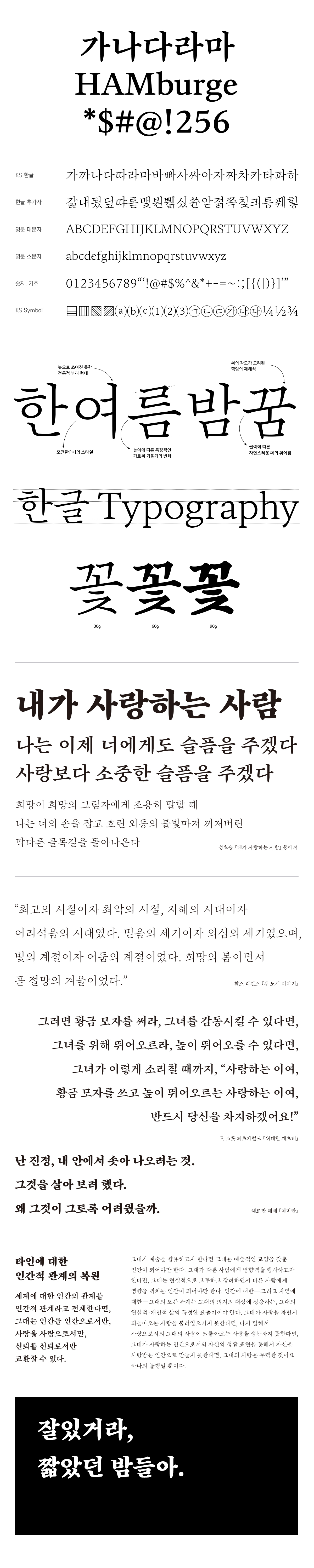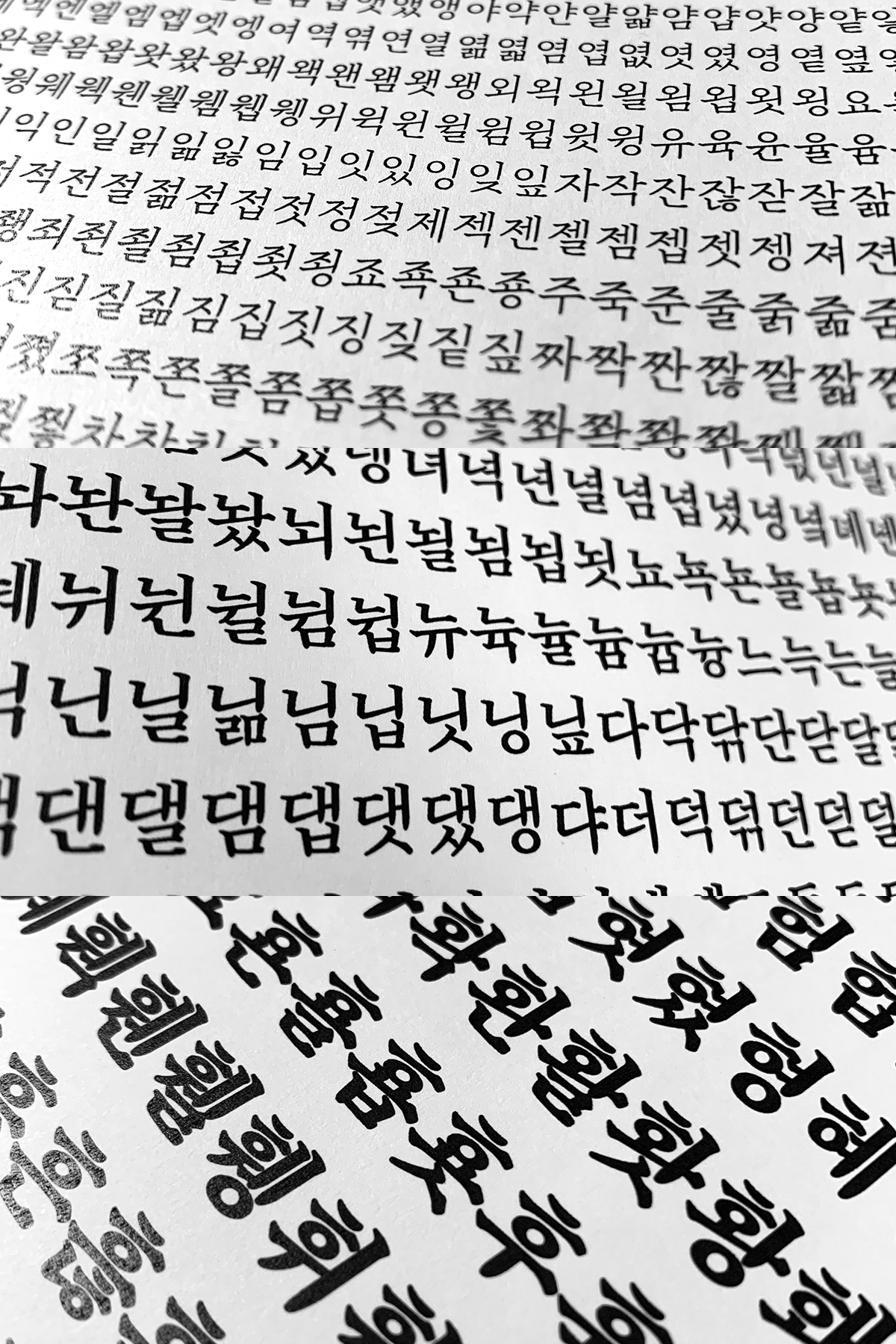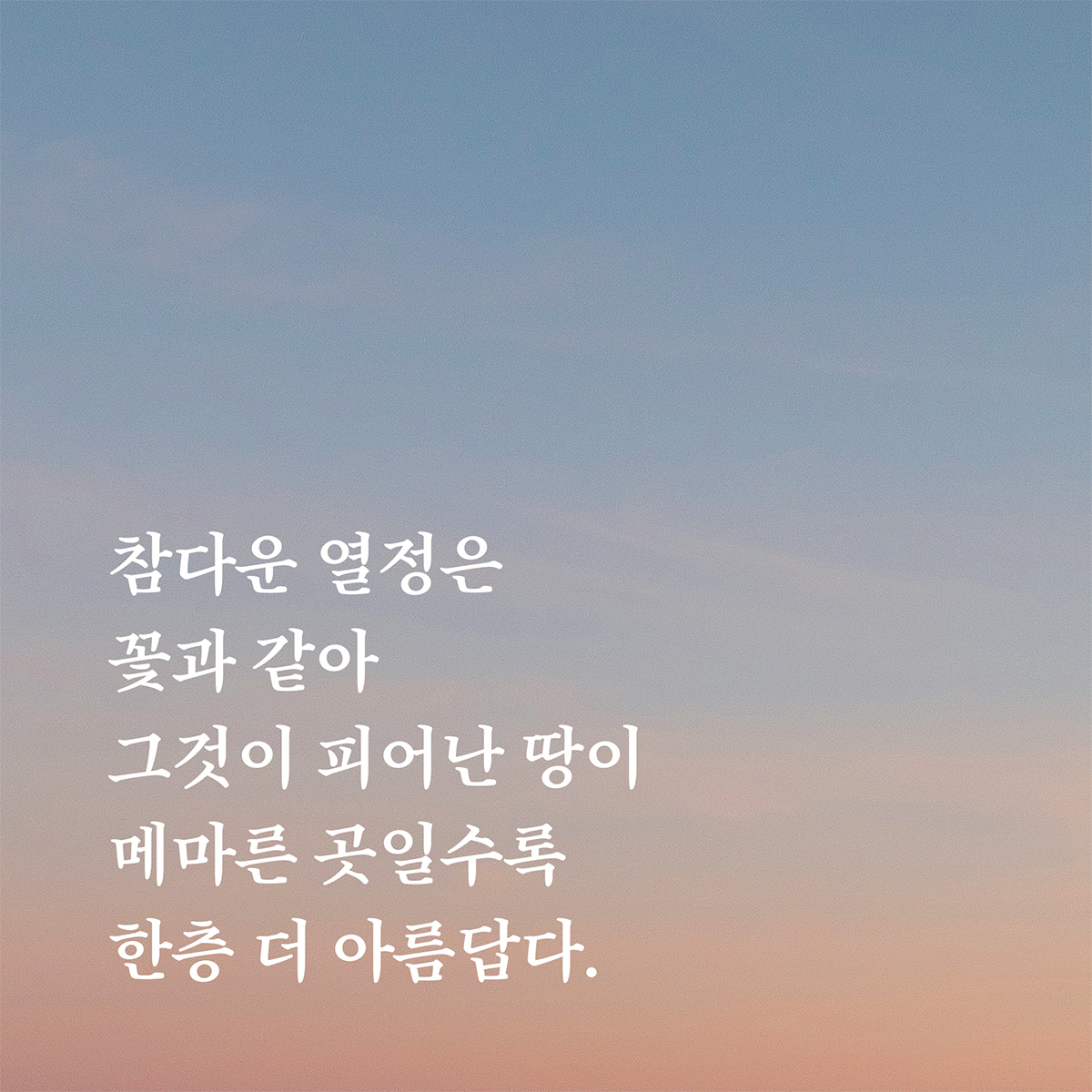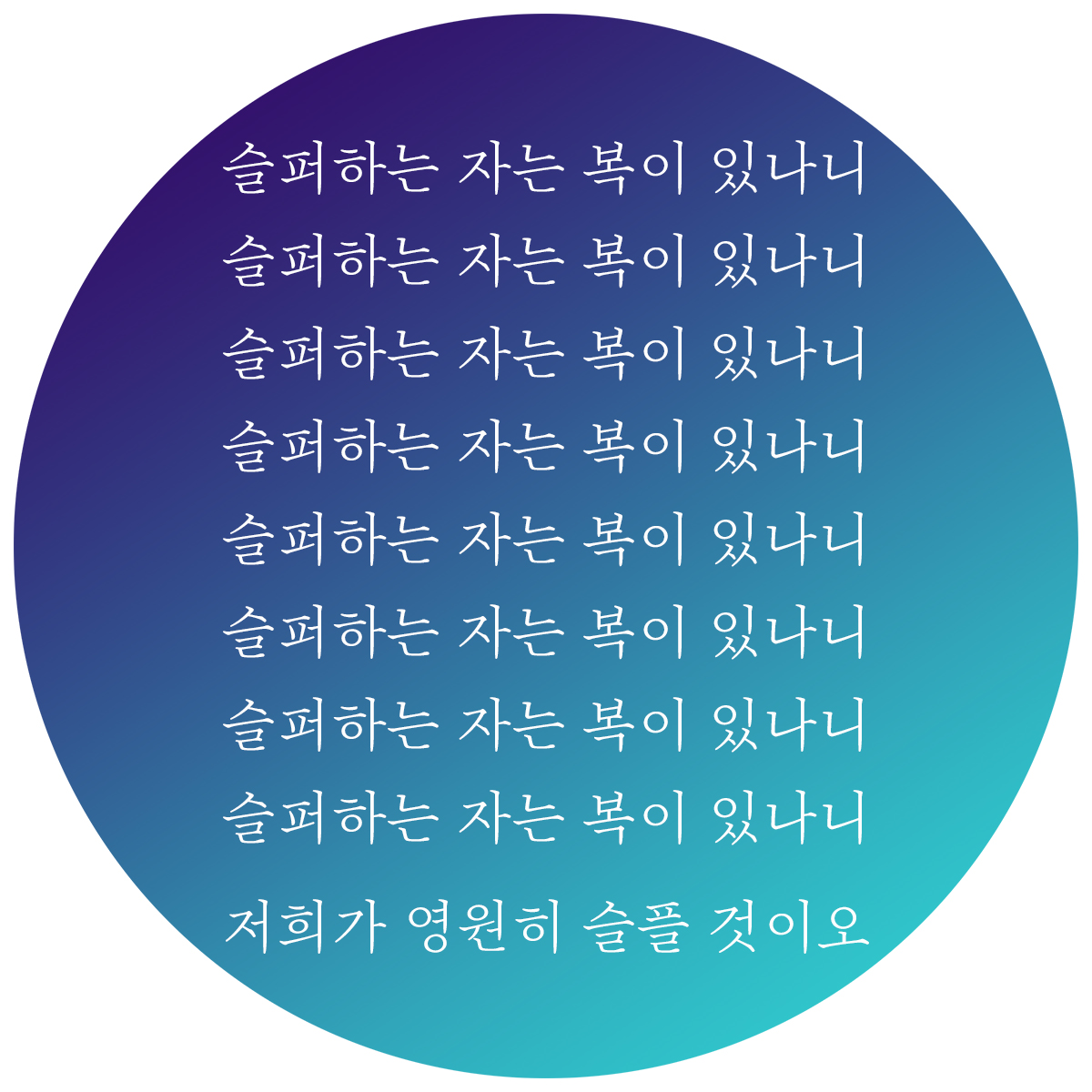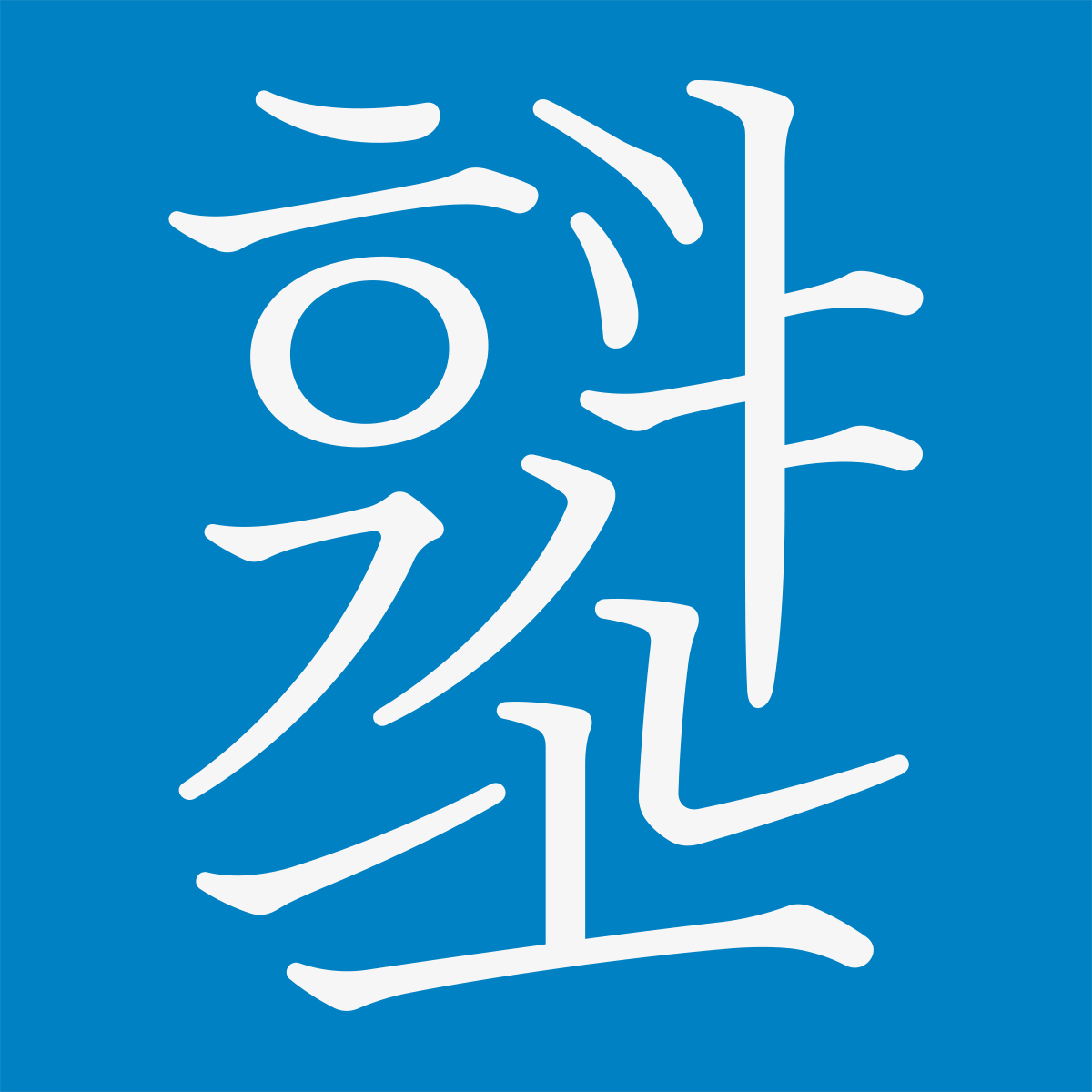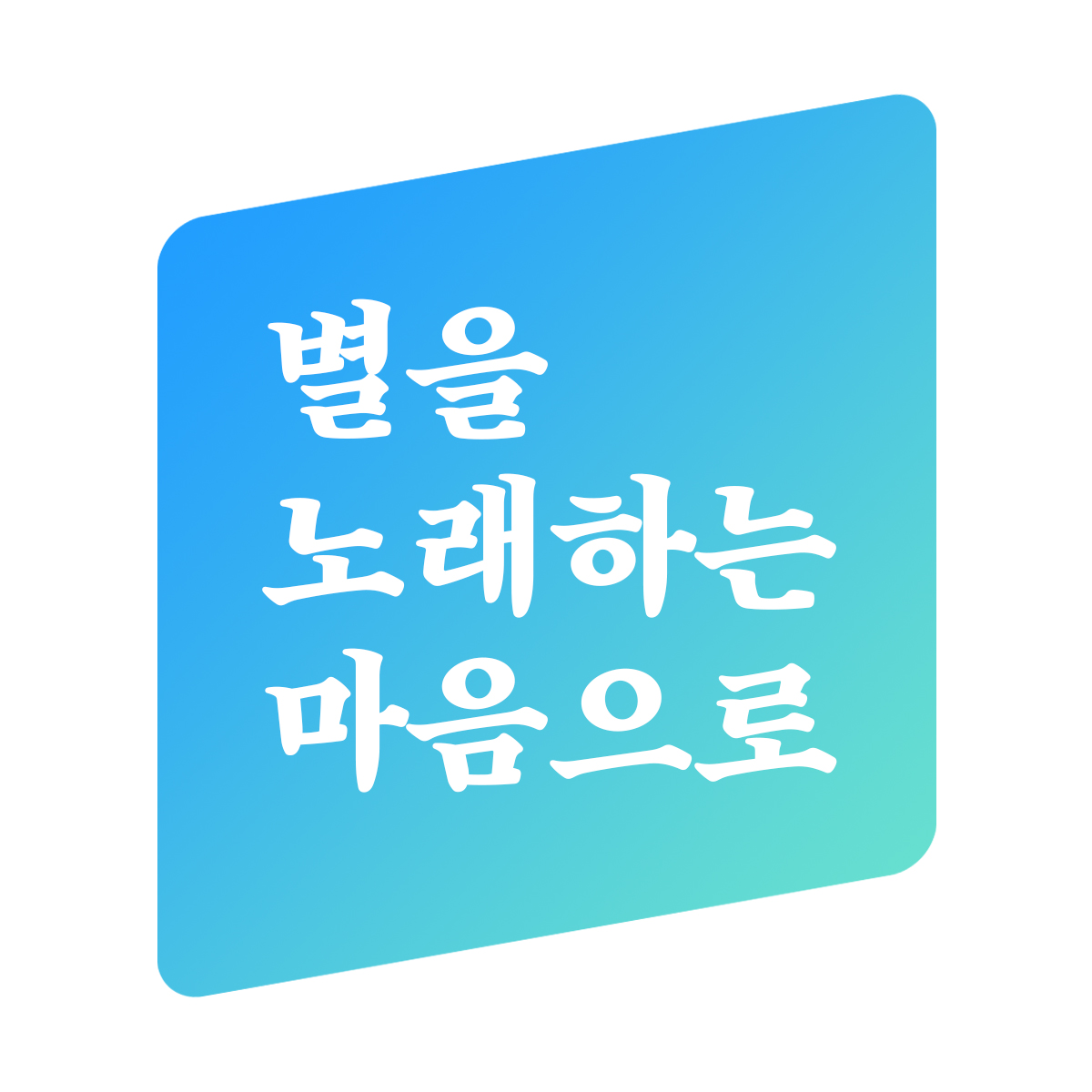
3가지 웨이트의 패밀리로 구성되어 있으며, 11,172자의 한글 글립이 모두 디자인되어 있습니다. 낱글자의 형태와 구조가 비교적 다양하게 디자인되어 있어서 그에 맞는 글자 너비가 적용된 가변폭으로 제작되었습니다. 영문 디자인은 한글 궁서체의 획 순을 연구하여 영문 서체에 적용하였습니다. 때문에 일반적인 영문 서체의 디자인은 아니지만 HG씨앗체와 어울리는 영문 서체로 그려졌습니다.